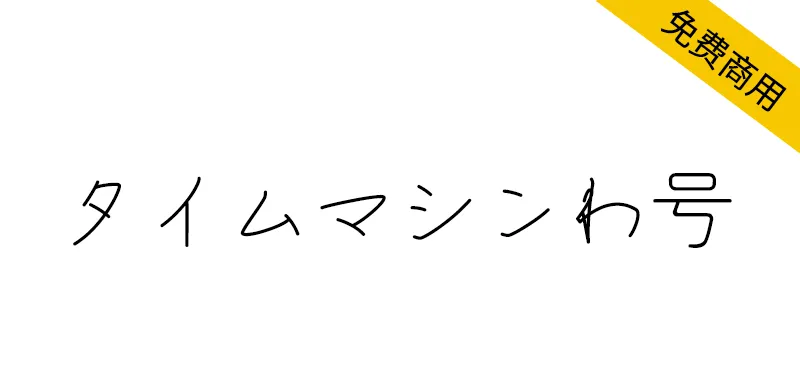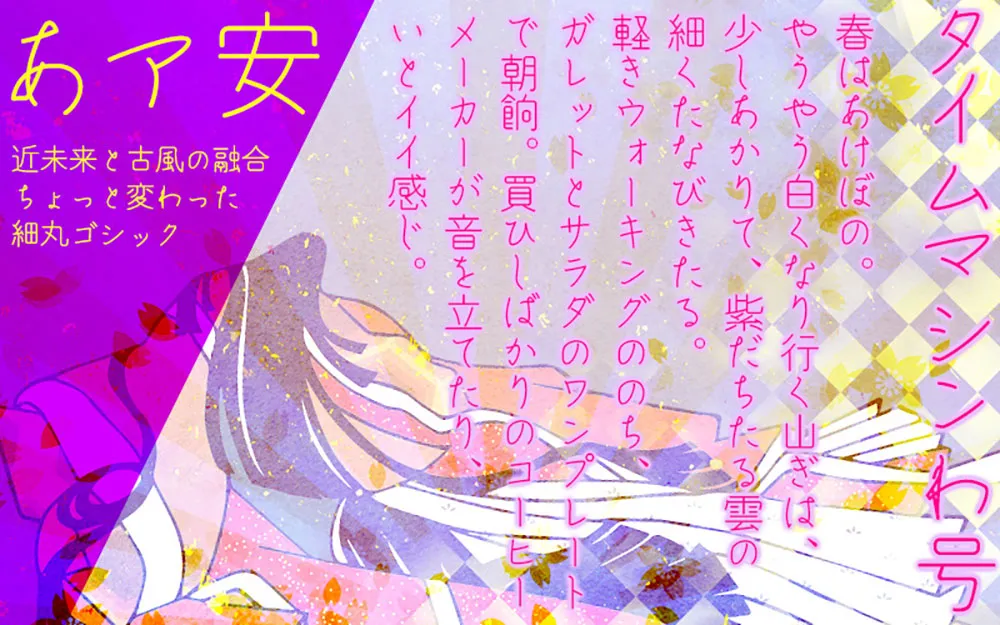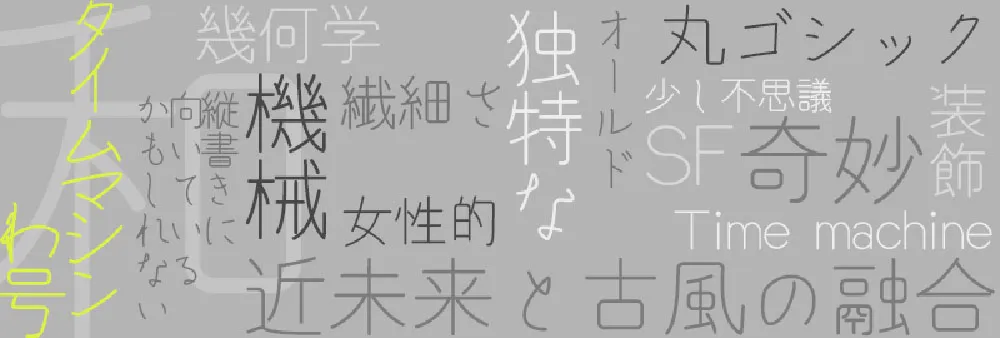
タイムマシンわ號介紹
タイムマシンわ號是和田研細丸ゴシック衍生字體,以和田研細丸ゴシック2004繪文字(稀土元素)為基礎,將原創的假名組合起來,整理而成。向和田研フォント及び、和田研細丸ゴシック相關人員表示深深的感謝。在算法半自動生成的獨特漢字中發現了科幻感,結合完全相反的古風假名,讓氣氛變得更加不可思議。
和田研細丸ゴシック派生フォントです。「和田研細丸ゴシック2004絵文字(希土類元素レアアース様)」を元に、オリジナルのかなを組み合わせ、アレンジしたものです。和田研フォント及び、和田研細丸ゴシック関係者各位に深く御禮申し上げます。アルゴリズムによって半自動的に生成されたという、獨特な漢字にSF感を見出し、真逆の古風なかなを合わせて、より不思議な雰囲気にしてみました。